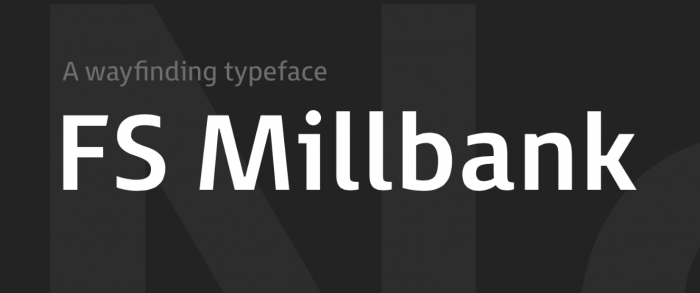
Fontsmith veröffentlicht neue Schrift: FS Millbank
Man müsste mal ausprobieren, wie dass bei Fließtexten mit der Leserlichkeit ist. Mir gefällt sie aber auch gut, sie hat eine schöne freundliche und moderne Anmutung.
Boah, danke für den tipp. Ein echtes Schmankerl. Und auch icons um längen tauglicher als diese und diese oder diese.
@stoetzner: was ist verkehrt an den pfeilen?
was ist verkehrt an den pfeilen?
a) die Pfeile haben zwei Spitzen statt eine
b) die Spitzen zeigen jew. in zwei verschiedene falsche Richtungen
Ich seh, wenn überhaupt, 3 Spitzen
Ist natürlich eine recht theoretisch-akademische Argumentation. In der Praxis werden sie genau so rasch wirkend wahrgenommen
wie die mit rechtwinkligen oder abgesofteten Schenkeln.
Ich seh, wenn überhaupt, 3 Spitzen
Ist natürlich eine recht theoretisch-akademische Argumentation. In der Praxis werden sie genau so rasch wirkend wahrgenommen
wie die mit rechtwinkligen oder abgesofteten Schenkeln.
Ich sehe ›nur‹ zwei Spitzen. Auch finde ich das mitnichten ein akademisches Problem, sondern ein ganz konkret graphisch-gestalterisches.
Das Wesen eines Pfeilzeichens ist Eine gerichtete Spitze. Diese Spitze dann aber als rechten Winkel auszubilden, das ist in meinen Augen ein theorieverhafteter Schematismus, vulgo Akademismus, der nichts bringt. Und daß die rückwärtigen Enden einer Pfeilspitze ganz besonders spitz werden, nur weil sie angeblich zwei parallele Kanten bilden müssen … mein Auge sagt da einfach nur AUA und mein Kopf sagt :zzzz: !
Könnte es sein, das unser Stotzner diese Spitzen entdeckt hat, und dadurch im Pfeil eine Richtungsanbgabe wie im rechten sieht, (wobei mir jetzt schon klar ist, dass hier die Pfeilspitern auch wieder so betrachtet werden könnten, das diese wieder jeweils in 3 Richtungen zeigen)post-22079-0-82406600-1421842760_thumb.p
Er hält das, was man normalerweise als Spitze bezeichnen würde, in diesem Fall nicht für eine Spitze, weil es sich um einen 90-Grad-Winkel handelt, und das ist schließlich, wie man so schön sagt, nicht wirklich spitz. (Dass ich das hier trotzdem wegen der Gesamtform als Spitze wahrnehme, muss ja nichts bedeuten.)
Ja, mit den zwei Spitzen meine ich die zwei spitzen Detailformen (wei von catfonts gezeigt). Weil sie durch ihre Spitzheit optisch einen stärkeren Reiz geben als andere Partien, ist für mich die Induktionswirkung, die ich eigentlich von einem Pfeilzeichen erwarte, beeinträchtigt. Es ist einfach unlogisch: was als ›Spitze‹ gemeint sein soll wird ein rechter Winkel und nachrangige sonstige Details sind dagegen spitz. Wozu soll das gut sein?
Wozu soll das gut sein?
Weil die so entstehenden Parallelen die Richtung betonen. Ich bin zwar auch kein Fan dieser an die alten Windows-Dingbats erinnernde Gestaltung, aber ich denke da hat jede Form ihr Für und Wider.
Weil die so entstehenden Parallelen die Richtung betonen.
ja, nur leider entstehen dadurch zwei ungewollte Pfeilspitzen, die fast genau in die Gegenrichtung deuten: Effekt aufgehoben.
Ich finde auch, dass das eine unnötig akademische Diskussion ist. Pfeile sind wie Buchstaben gelernte Symbole. Wir erkennen sie aus ihrer Gesamtform – ihrem Skelett. Es sagt ja auch keiner, man könne bestimmte Buchstaben nicht lesen, weil einzelne Strichenden mal schräg, rund, rechtwinklig oder mit oder ohne Serife enden. Der Einfluss solcher Gestaltungsvarianten ist marginal und fällt somit eher in den Bereich der Stilentscheidungen.
Zudem ist die Gestaltung der obigen Pfeile ja auch nicht exotisch, sondern entspricht zum Beispiel den ISO-Pfeilen, die weltweit millionenfach benutzt und täglich millionenfach gelesen werden. Und da gilt dann auch wieder: We read best, what we read most.
In den Ecken sehe ich beim besten Willen keine Pfeilspitzen, allein schon, weil sie nicht den Verlauf der vorhergehenden Linie weiterführen – im Gegensatz zu der 90°-Spitze.
Sorry, lieber Stötzner, aber ich muste für meine Zeichnung schon ordentlich Quer denken, um auf die von Dir entdekten Pfeilspitzen zu kommen. Tatsächlivh handelt es sich hier - betrachtet man dies als echte Pfeilspitze - um die Wiederhaken des Pfeiles, das ein herausrutschen aus dem Ziel verhindern soll. Schaut man sich alte, echte Pfeile an, so sind diese entgegen der Flugrichtung weisenden Ecken oft auch viel spitzer, als die eigentliche Pfeilspitze:
ja, nur leider entstehen dadurch zwei ungewollte Pfeilspitzen, die fast genau in die Gegenrichtung deuten: Effekt aufgehoben.
Das ist Deine Interpretation. ;-)
... um die Wiederhaken des Pfeiles, das ein herausrutschen aus dem Ziel verhindern soll. Schaut man sich alte, echte Pfeile an, so sind diese entgegen der Flugrichtung weisenden Ecken oft auch viel spitzer, als die eigentliche Pfeilspitze:
Dieses Bild zeigt eine phantastische Form und ist das beste Beispiel zur Stützung meiner Argumente. Hier gibt es eben nur eine Spitze und zwar vorne, dort wo sie hingehört. Die Widerenden sind abgerundet! Außerdem hat die Form insgesamt eine gestreckte Proportion, was für die Deutlichkeit eines Pfeilzeichens auch visuell sehr wichtig ist.
Ich verstehe was Du meinst und bin auch kein Freund dieser Formen, jedoch denke ich das dies einfach eine Frage der Ästhetik ist und im praktischen Einsatz keinen Unterschied macht.